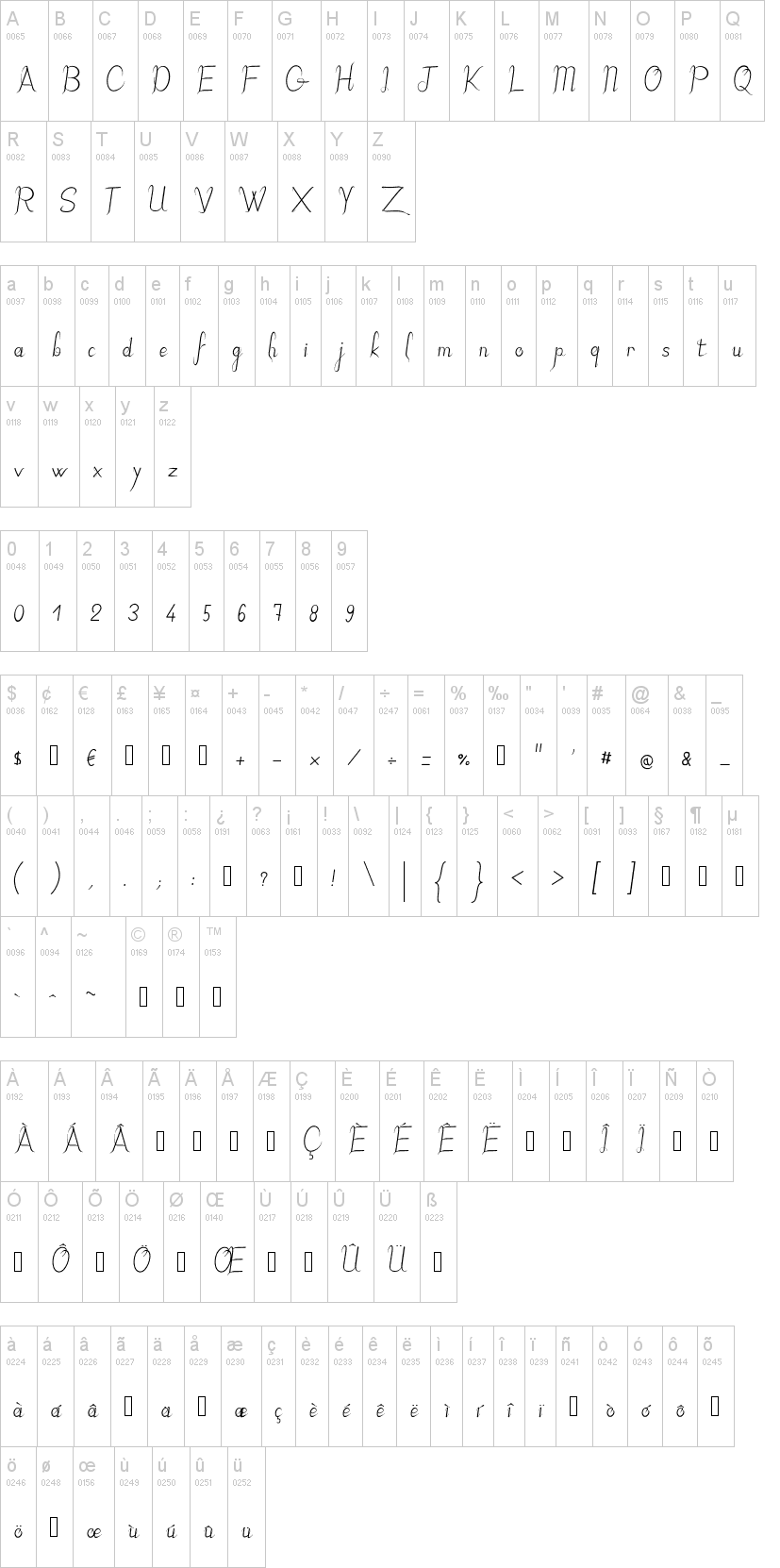
JB Elegant 是一款简洁大气的英文字体,它有着优雅的外形,细腻的线条,以及清晰的字母结构。它适合用于各种类型的文档,如新闻报道,广告,宣传册,网页,海报等等,可以让文字具有高贵的气质。此外,JB Elegant 字体还具有较高的可读性,可以让您的文字更加清晰易读。内容介绍
JB Elegant是一款非常不错的手写艺术字体,具有很好的视觉感,适合于文化类的宣传设计、商业类品牌的广告和产品包装设计以及个性化文字排版等较多场景。